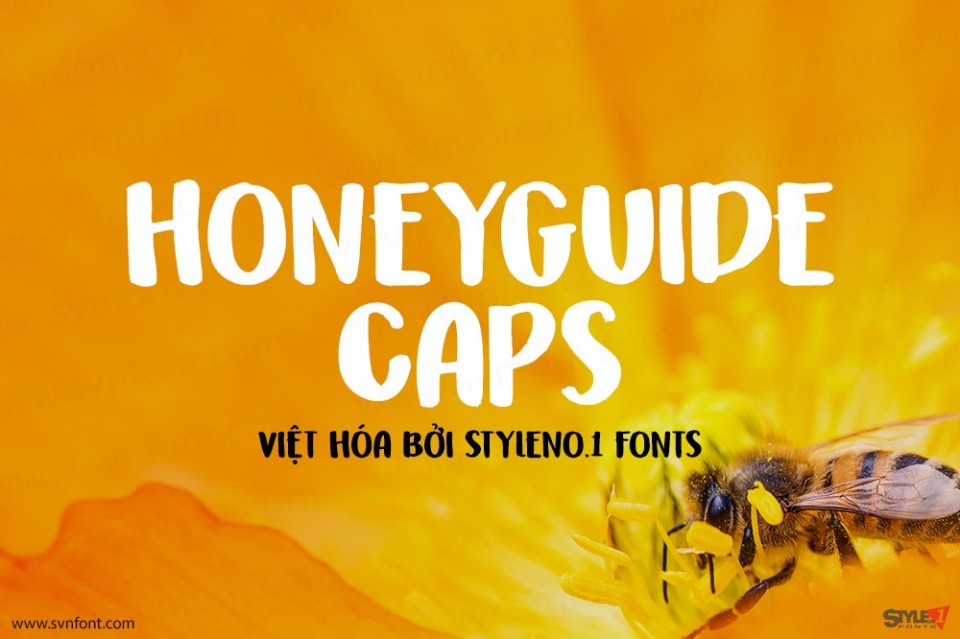
Font việt hóa SVN Honeyguide Caps
Trong thế giới đồ họa hiện nay, việc lựa chọn một Font Miễn Phí chất lượng đóng vai trò vô cùng quan trọng để tạo nên cá tính riêng cho tác phẩm. Font việt hóa SVN Honeyguide Caps là một cái tên nổi bật trong danh sách các bộ phông chữ trang trí mạnh mẽ và độc đáo. Được thiết kế dành riêng cho các tiêu đề lớn, bộ font này mang lại cảm giác hiện đại, phóng khoáng nhưng không kém phần tinh tế. Với sự hỗ trợ đầy đủ các ký tự tiếng Việt từ nhóm SVN, người dùng có thể tự tin sáng tạo mà không lo lỗi hiển thị hay thiếu hụt dấu câu trong quá trình làm việc.
Ưu điểm nổi bật của Font việt hóa SVN Honeyguide Caps
Phong cách thiết kế đặc trưng
Font việt hóa SVN Honeyguide Caps sở hữu những đường nét dày dặn và bố cục cân đối, rất phù hợp cho các dự án yêu cầu sự nổi bật và dễ đọc. Kiểu chữ All Caps này giúp các thông điệp trở nên quyền lực và thu hút ánh nhìn ngay lập tức. Đây là lựa chọn lý tưởng cho các bạn học sinh, sinh viên khi làm báo tường hoặc thiết kế bìa tiểu luận. Font chữ này không chỉ đẹp mà còn mang lại sự chuyên nghiệp cho những ai mới bắt đầu học thiết kế đồ họa.
Ứng dụng đa dạng trong thực tế